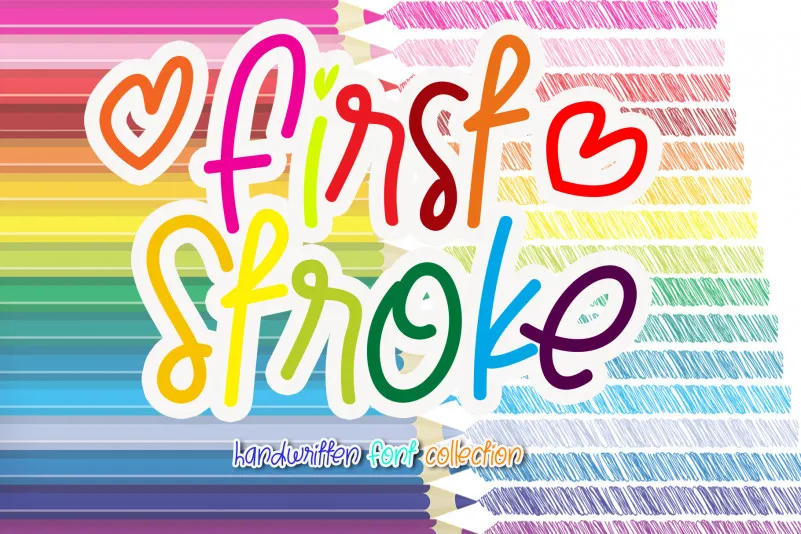
First Stroke Font – Download Grátis
Esta é uma linda e rica fonte escrita a mão que se destaca por sua forma redonda e flexível. Com seu tom quente, peculiar e animado, ela transformará suas ideias para projetos em verdadeiros trabalhos de arte. Esteja à vontade para explorar as inúmeras variações desta bela fonte e divirta-se com ela. É uma ótima opção se você estiver procurando um visual agradável que enriqueça seu design de qualquer maneira. Seja um convidado especial nesta fonte de estilo display da Kateengciu, disponível na categoria de fonts para projetos visuais criativos.